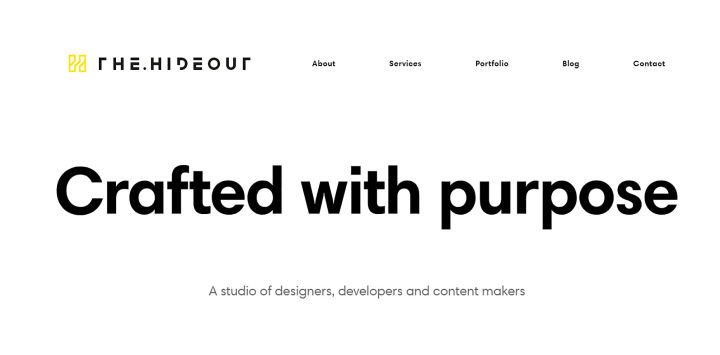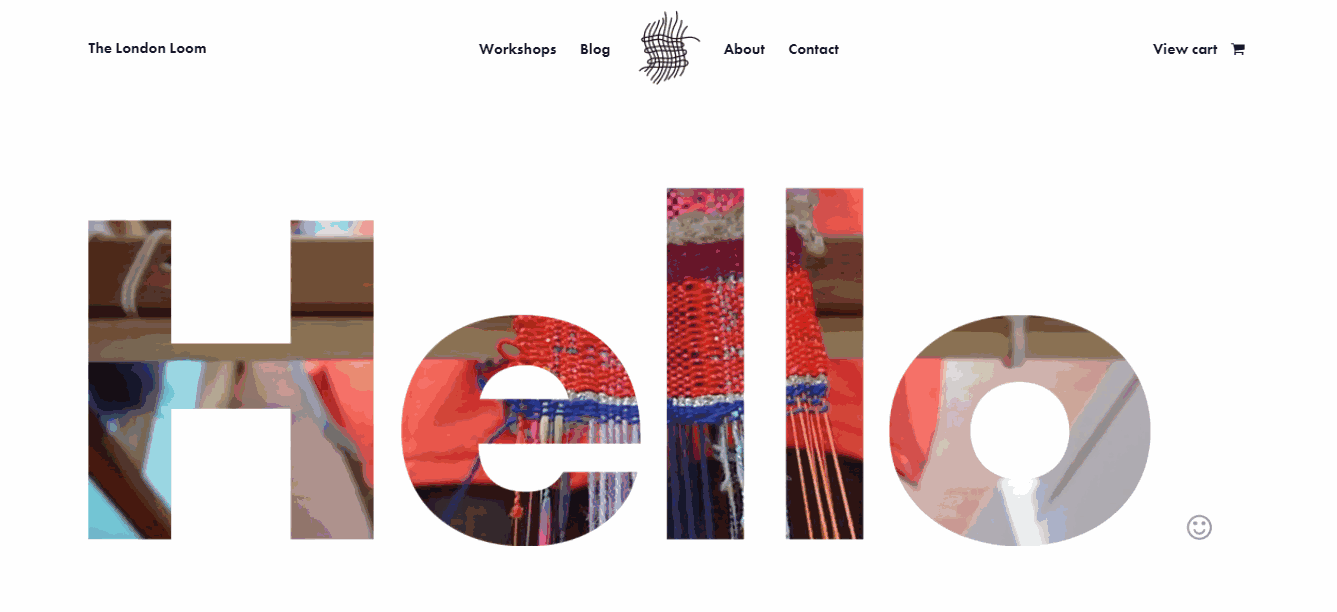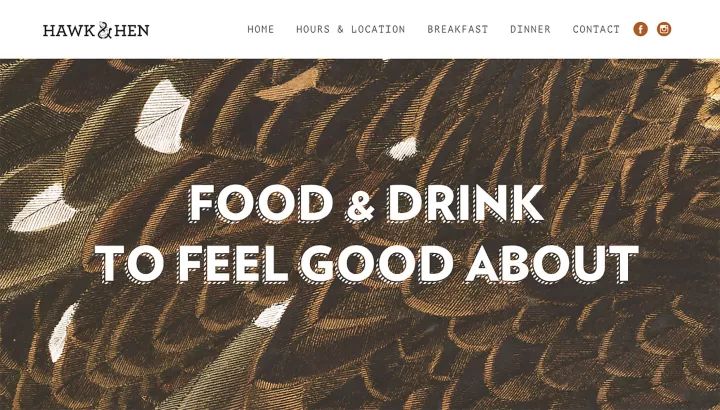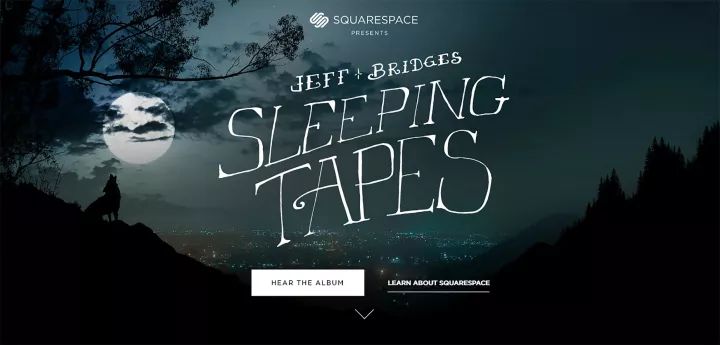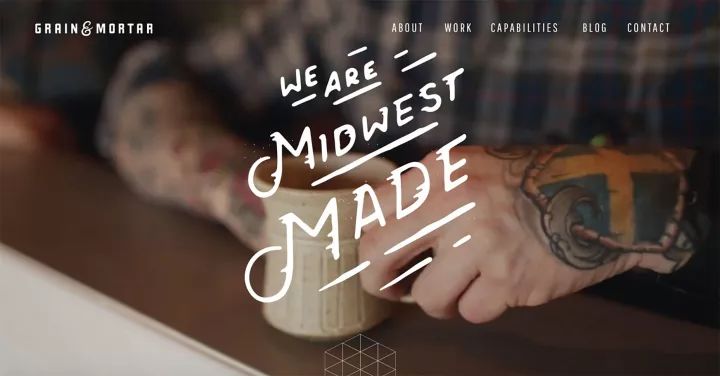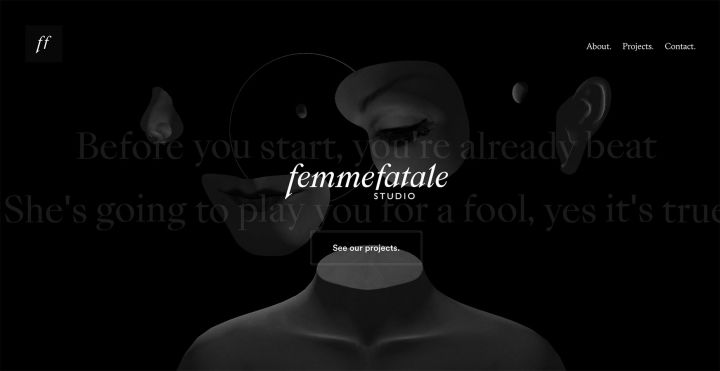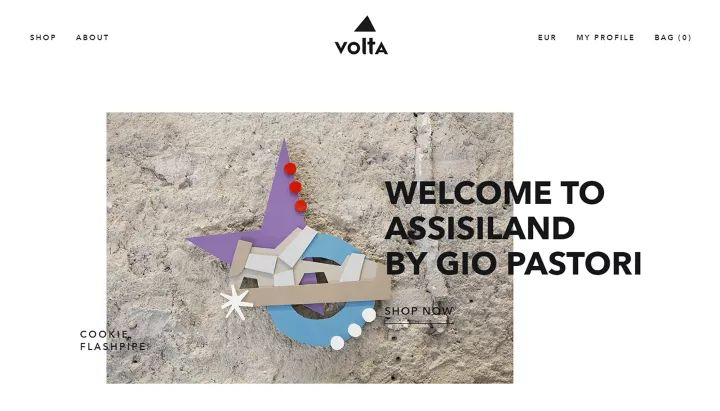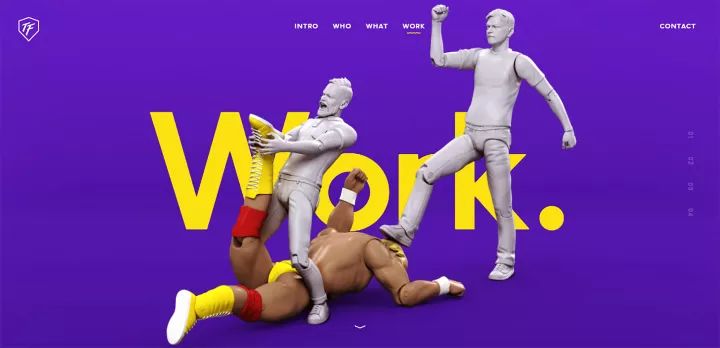
字体设计策略,5种展示性字体创造独特戏剧效果的技巧
无论是设计网页还是移动端APP,首页、首屏、Banner 这些地方,绝大多数时候都需要设计感较强、视觉元素丰富、具备明显吸引力的视觉设计,来作为支撑。有的项目可以依靠惊艳的图片,更多的设计师会选择多元素的图文混排,而这其中,字体是关键元素之一。
展示用的字体不仅要具备展示性,还要拥有良好的可读性。展示性意味着它需要能够在特定条件下创造出戏剧化的效果,通过屏幕上的展示,吸引用户的注意力,向着屏幕另一端的用户传达出特定的信息和感受。所以,合理地运用展示性的字体不仅能够强化品牌形象,增强文本内容的可理解性,创造视觉层次,给用户留下深刻的印象。近年来,展示性字体的需求越来越大,个中缘由也就不难理解了。
今天的文章会总结5种使用展示性字体创造独特戏剧效果的技巧,帮你的页面在激烈的竞争中,脱颖而出。
1、简约但动感的字体
简约的字体和动感的排版并不是互相排斥的存在。事实上,简单的字体同样可以轻松创造有着强力戏剧感的排版。事实上,你只需要选择一款足够简约的字体,然后按照下面的方法来处理:
・使用超大的字体尺寸(大字体能够传达出足够有力的信息,尤其是和高清大图配合使用的时候)
・文字色彩和背景构成对比(文本色彩通常会使用黑色或者白色,而背景图片足够鲜艳就能构成对比)
・采用大胆的样式
字体大小是控制视觉影响力的重要手段。在下面的案例当中,设计师采用了更为极端的方式,使用超大的字体来承载主要的文案,借助留白将文本孤立出来,以达到有效传递信息的目的。这样的设计足够简约,但是也充满了强烈的戏剧感。同时,清晰直白的设计,也让人印象深刻。
2、创造性地使用简约的字体
即使是最基础、最简单的字体也可以创造出令人难忘的体验,前提是你得采用实验性的、富有创造性的排版。
想要将你的信息大声地传递出去吗?使用全部大写的文本,或者借用足够厚重的字体。而真正让人难忘的,是足够富有创意的设计,所以,你还可以将字体和动效或者视频结合起来使用。
3、装饰性字体
设计师对于装饰性字体的认知各不相同。有的设计师会鄙视装饰性的字体,认为它们显得粗陋轻佻,但是也有不少设计师会欣赏这些字体所体现出来的创意和有趣的表现形式。在我看来,各种稀奇古怪的装饰性字体,如果使用得当,能够让网站增色不少。
这些字体可以调和网站的风格,营造氛围,能够强化品牌的气质。当设计师挑选了合适的字体,结合贴合品牌的文案和风格之后,整个体验会达到协调甚至出彩的效果,下面就是几个值得参考的实例:Hawk&Hen 是一个餐饮机构的网站的,略显复古的立体装饰性字体为网站奠定了古怪但是独特的风格。
经过定制的字体错落而怪异,非常符合 Squarespace’s Sleeping Tapes 阴森而黑暗的网站风格。
HeadOfffice 的网站所采用的这套字体同样俏皮而独特,在绝大多数场景下,这套字体都显得过于特立独行,但是在这个网站上,则正好烘托出网站充沛而富有激情的特征。
Maaemo 的首页所采用的这套字体带有明显的现代几何风,字体的细节带有早期西文字体的原始风貌,和网站的神秘气息相得益彰。
你可能已经注意到了,这些网站中,装饰性字体始终是和极简的风格相互搭配。这不是巧合。装饰性字体能带来独特而有趣的风格,在极简风格的网站上,用户会更加轻松地注意到这些字体的存在,信息才能更加有效地传递出去。假使这些字体在复杂多变的网站上,多个视觉焦点会分散这些装饰性字体应有的力量。
4、手绘字体
在很长的一段时间内,手绘字体都是网页设计中的重要组成部分。有的设计师会倾向于逐个字母单独设计,创造出独一无二的手绘字体效果,不过更多的时候,设计师会选取一款成套的手绘风格字体作为基础来设计。
手绘字体通常能够让整个设计显得更加优雅,如果挑选得当的话。独一无二的手绘字体还能强化页面的原创性,看看下面的 Grain&Mortar 和 Femmefatale 两个网页,这些设计机构的首页本身所呈现出来的“艺术性”很大程度上源自于页面中独特的手绘字体。
手绘字体是品牌化设计强有力的工具。
不过,千万不要过度追求漂亮的效果而牺牲字体本身的可读性。为了防止潜在的视觉障碍,尽量不要将手绘字体置于复杂的图片背景之上,并且在辅助性的文本中,采用识别度更高的字体。
5、和其他元素叠加使用
通过将字体和其他的元素叠加到一起使用,创造出引人瞩目的视觉效果,是时下所流行的另外一种营造视觉奇观的策略。不过,在搭配其他元素的时候,一定要注意色彩、纹理和元素各方面的特征,确保字体本身的识别度。
你可以让文本和多种不同的元素组合起来。
也可以让文本横跨不同的区域。
甚至可以打破排版规则,让文本和人物形象结合起来,让文本传递隐藏的意义。
但是无论怎么搭配,你都得让文本本身和其他的元素之间具备明显的对比度,让它足够易读。只有达到这样的要求,才能让整个体验足够顺畅,不至于出现使用障碍。